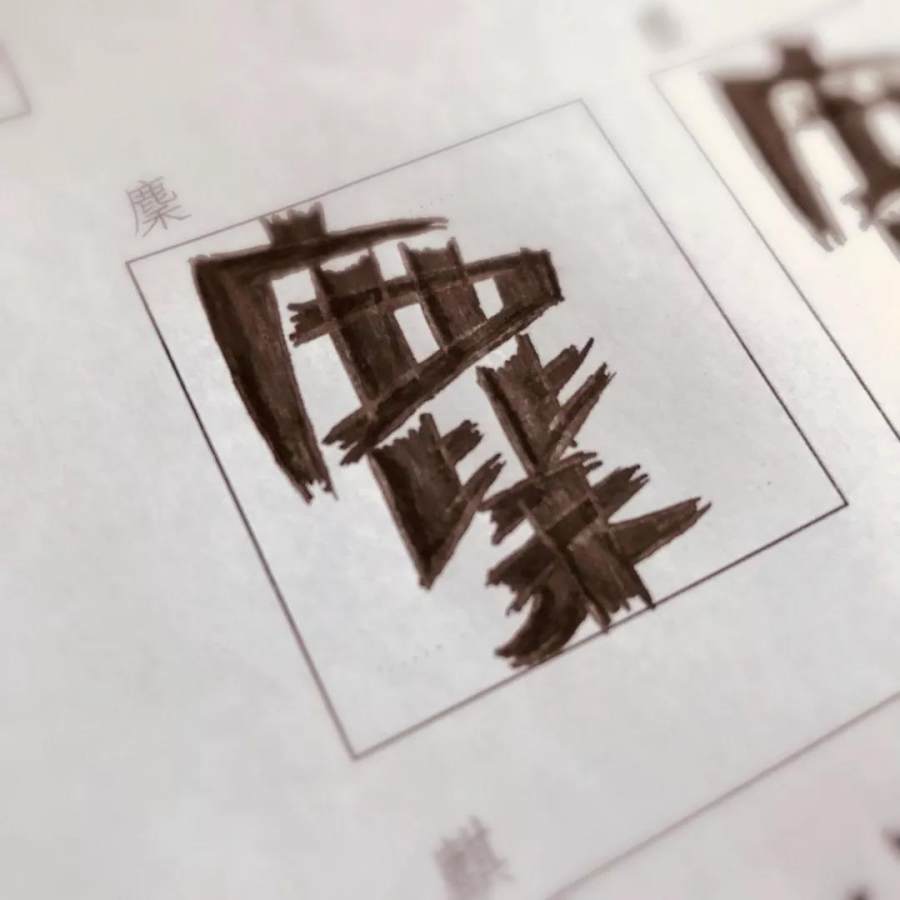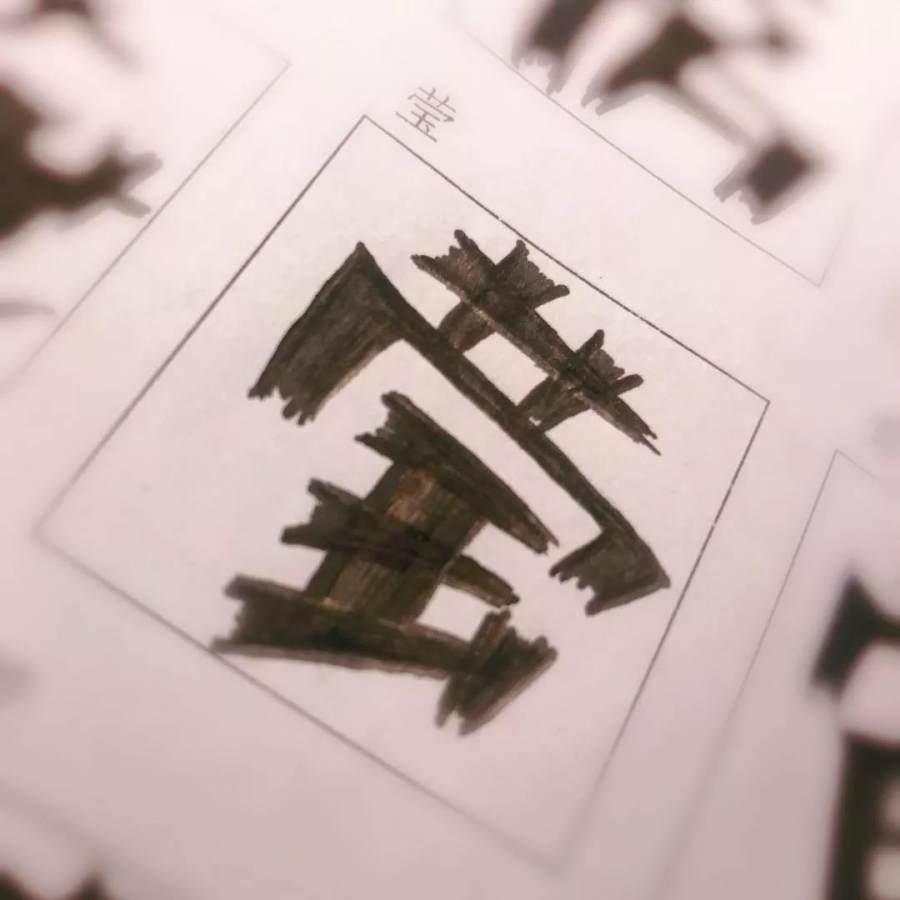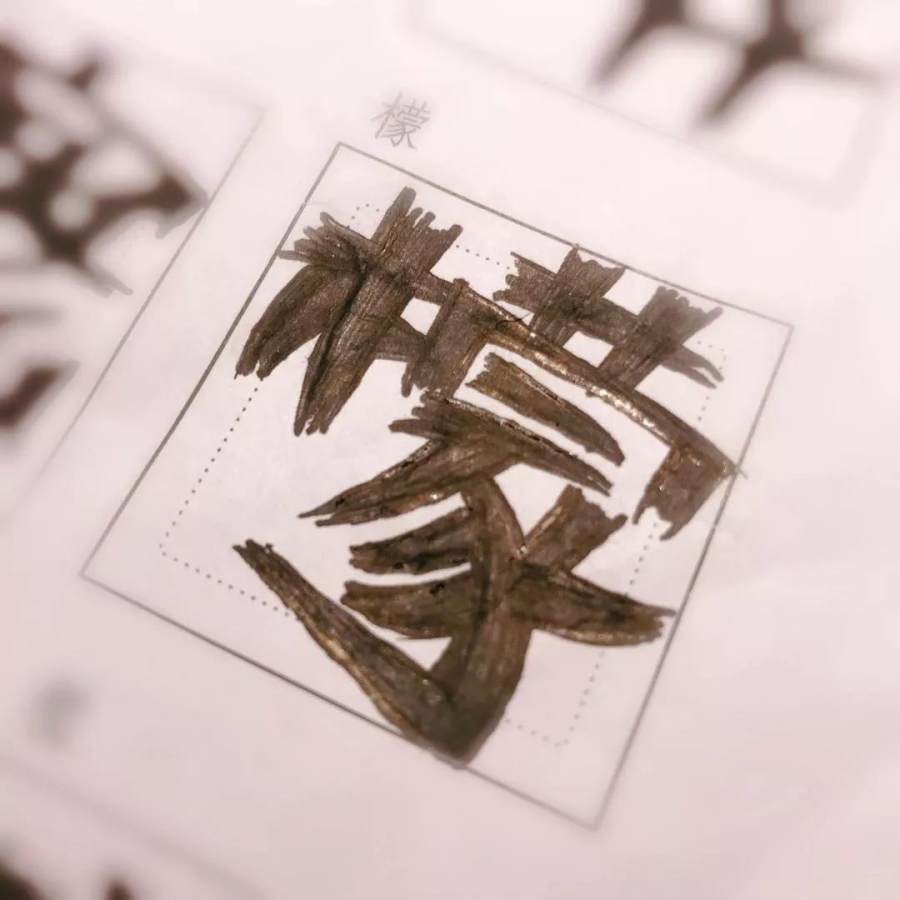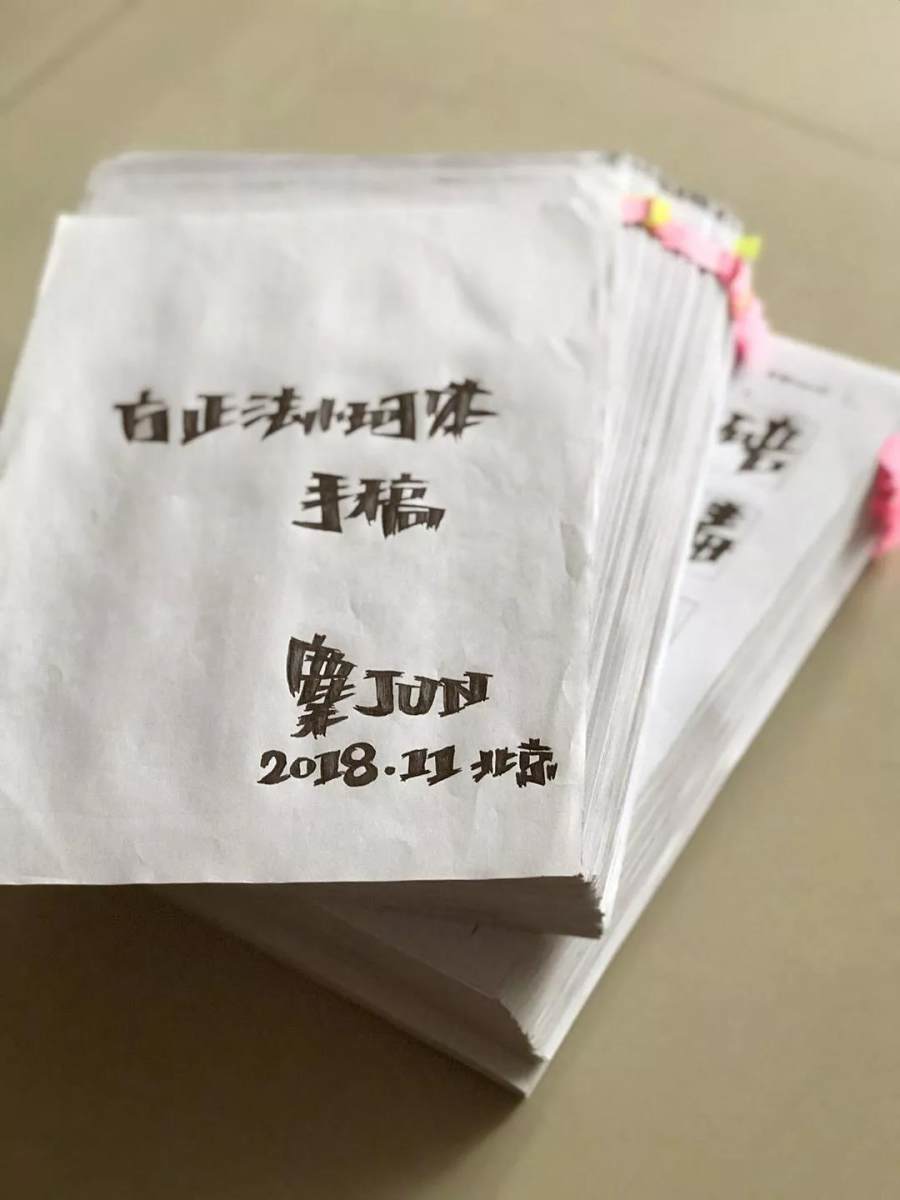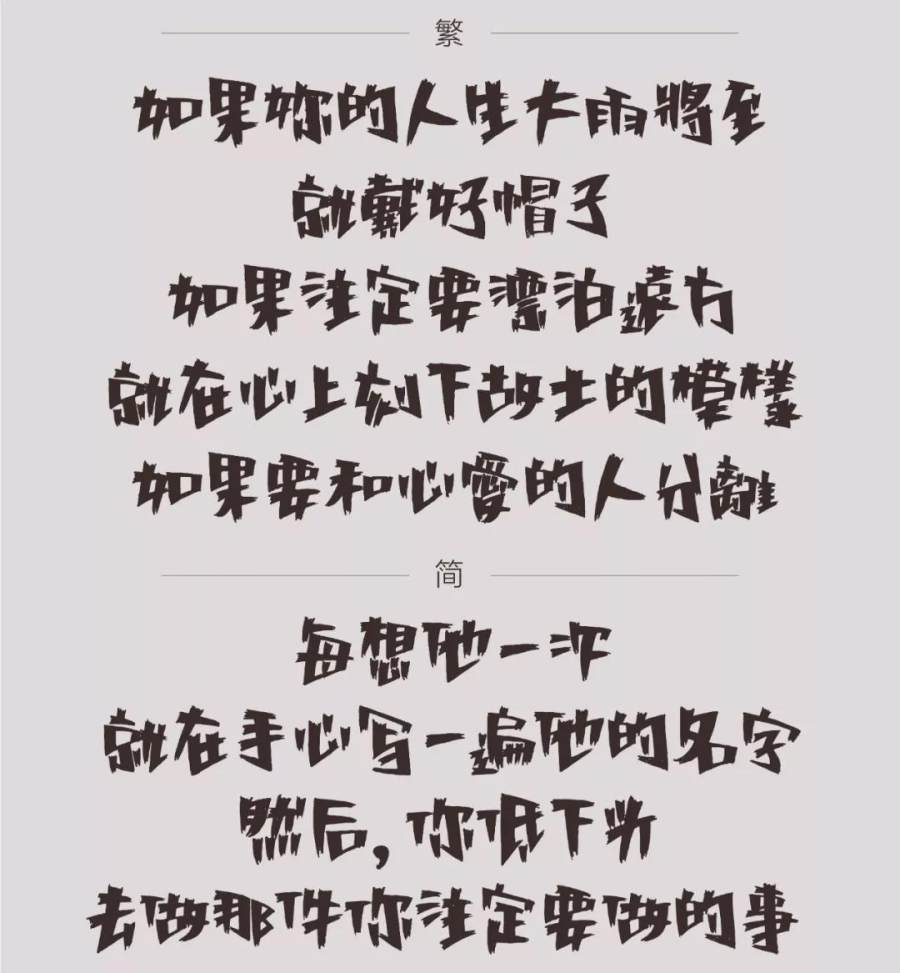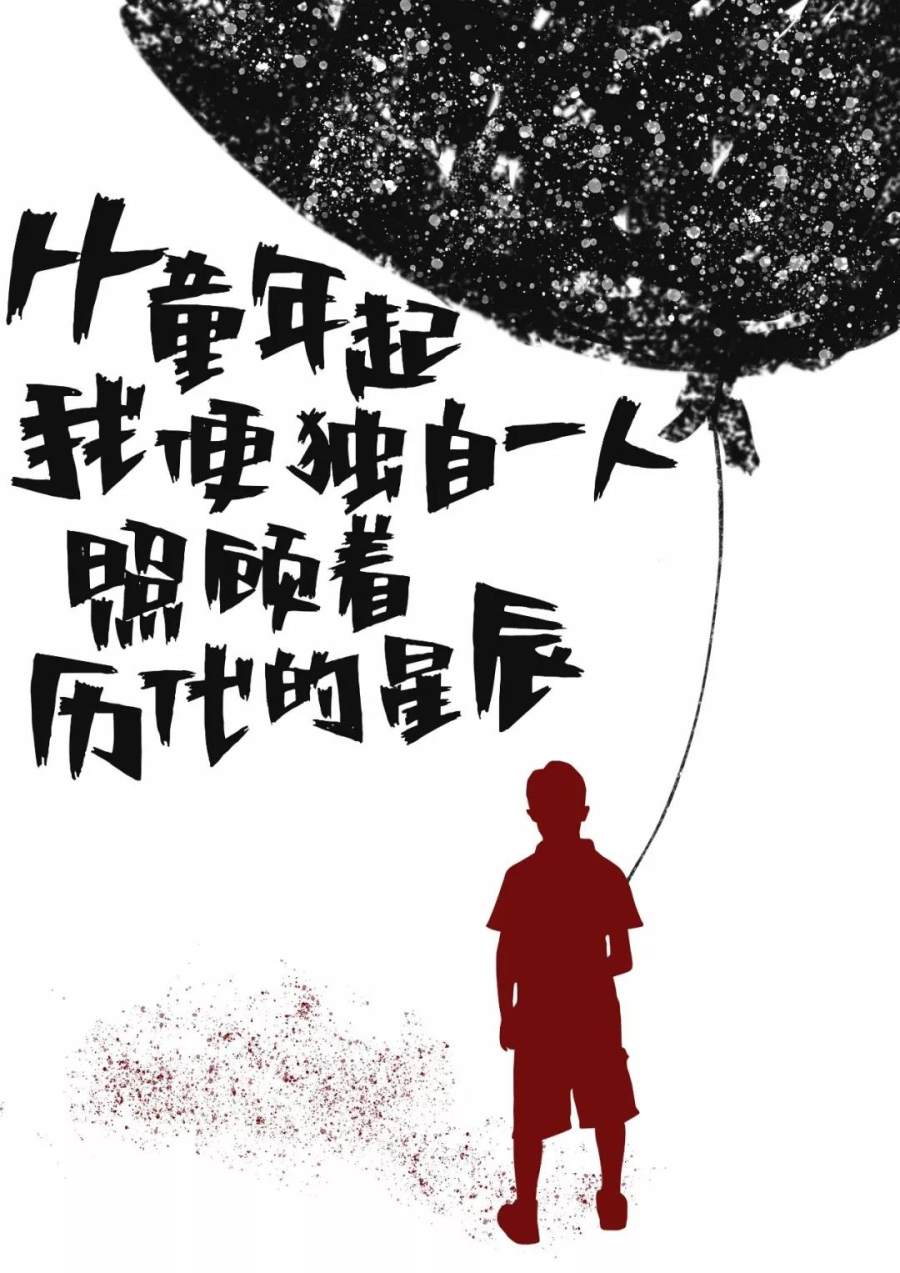
方正法小珂体 | 一款任性的洒脱,克制的浪漫手写体
有人说,字体设计是一门手艺活,需要设计师有精湛的技艺、专注的内心、耐得住寂寞,日复一日地推敲、打磨。
但更多时候,字体设计是一件微妙而浪漫的事情,
设计师们无不倾注了细腻的情感和十二分热忱,收获的也往往是常人体会不到的快乐和浪漫。
方正法小珂体的创作就是一段集理性、专注与挚爱、感性于一体的浪漫之旅。
原本是翻译爱好者的法小珂(李军麇jūn),因热爱写字,又多了一个字体设计师的身份。
在一笔一画间她感受到了字体设计工作的不易,在反复修改中她体悟到了字体设计的使命。
有着一颗文艺心的她,
用只言片语记录下了与方正字库合作开发字体过程中的点滴心路。欣喜、艰辛、坚持、匠心……尽在笔端。
#2017年8月9日#
可能会有一套自己的手写字体啦。
说起来,这件事既奇妙又温暖。
奇妙的是,我不是设计师出身,像半路被神仙抓走了。
温暖的是,写字(可能叫画字更合适)这件事我喜欢了20年,如今它能帮助更多的人。
▲ 用彩铅创作书写的“见字如面
▲ 法小珂早期创作的“字然系列”部分作品
#2018年2月7日#
下决定用签字笔涂写第一个字
带着沉沉的负重感,
万里长征,终于迈出了第一步。
它如此重大,所以我没把它当回事儿。
——苗炜《寡人有疾》
▲ 褪了色的“村上春树式自律”字条,一直贴在法小珂写字用的升降桌左上角位置
创写过程中第一次的沮丧时刻:不知道该如何处理一个字的偏旁写法
“禾木旁”,
是自己名字的用字,理应熟悉,但是不满意。
心中预感,大概需要返工吧。
▲ 最后定稿的“麇”(jūn)字
字体创作的一点小心思
遇到喜欢的人的名字用字时,会故意写好看一点,
当Ta 用到这个字时,会感受到那个字和其他字在感情上不一样。
▲ 作者两个好朋友的名字用字,两个字稿所用的纸张有区别,
带虚线框的纸是后来再次打印的,这部分的字稿全部重写了
又一个冬天,去方正字库交作业
北京泠冽的冬日清晨,
去交“作业”,回来就发烧了。
可能写了太久,停下来就会生病。
方正法小珂体手稿终稿,一共500页
把创作期间所有的纸、笔、字稿整理好收集起来,和自己说:都过去了
800页纸,
185支签字笔芯。
因为写字时太用力,每一页纸都洇过去,
翻过来,能摸得出被笔迹侵蚀过的凹凸感。
▲  打底稿用的5B铅笔,每一支几乎都被磨平了
▲ 185支签字笔笔芯,正是用它们写完了所有字稿
根据方正字库团队的专业建议进行增补、修改字稿的工作,革命尚未成功
擦铅笔底稿时,发现非常累人,
想不起当时是怎样擦完了500页手稿。
后来才恍然大悟:
是母亲偷偷帮我擦完了几乎所有要修改的部分。
▲ 上学时买的橡皮擦,十几年没用完,这次终于说再见了,后来又擦完一块新的
从字体创意到最终完稿,作者法小珂前后创作了15个月,每天8小时。
加上方正字库团队的后期制作,一共历时两年。开始写时还是炎炎夏日,交稿时迎来了又一年的大雪纷飞。
回忆起那段日子,她觉得自己像个木匠,
在深山打磨一件木器,日出而作,日落而息,期待着它最终的样子。
如今方正法小珂体终于付梓成库,与大家正式见面。
方正法小珂体,从字形来看并不规矩,如同长歪了的树,
每个字都打破传统字形规范,重心右倾,左右上下各部分大小比例鲜明,
却生出自有的平衡体系和风格。
兼具笨拙 、直率、质朴、随性、懒散、童真,枯笔效果可能还带出一点飒。
这款字包含常用简繁体汉字及基本符号9938个。
尤其适用于独立,喜与众不同,文艺情怀爱好者,应用于标题,包装,海报,广告,文化印刷品及周边。
应用展示